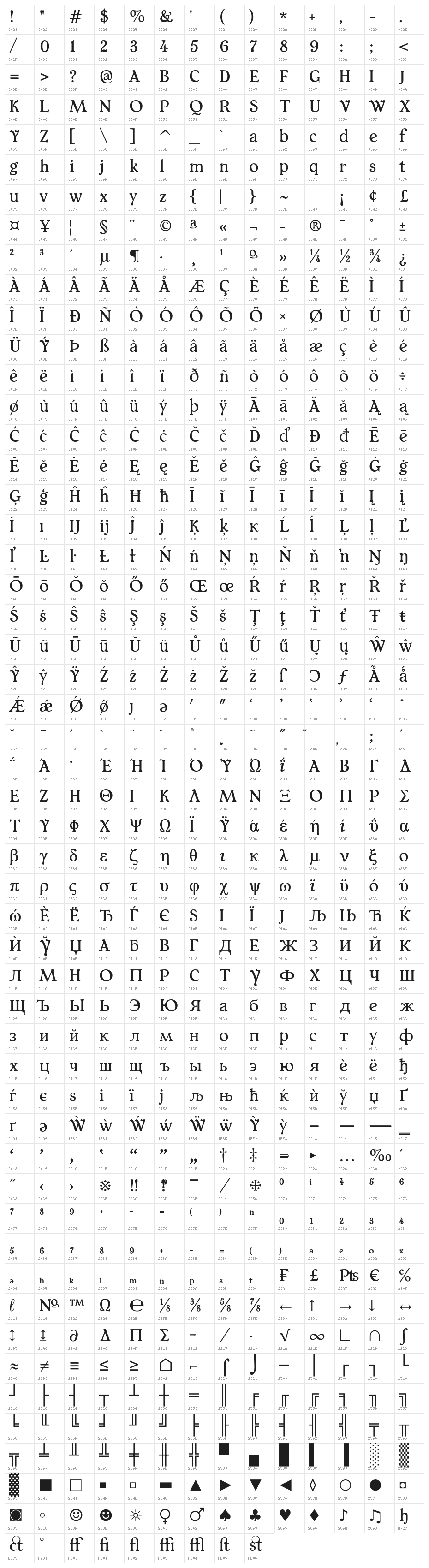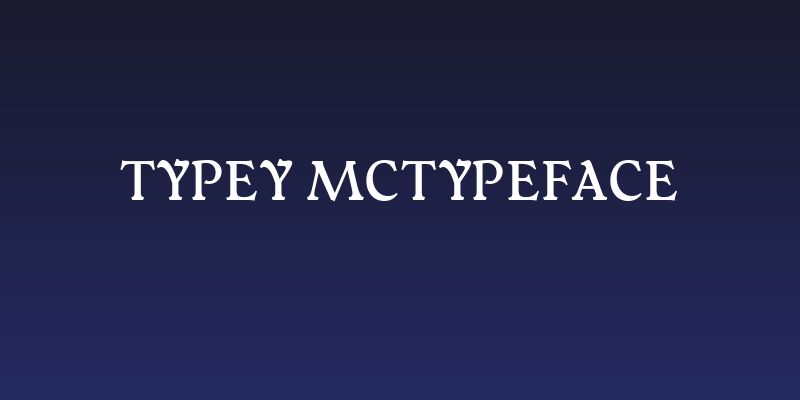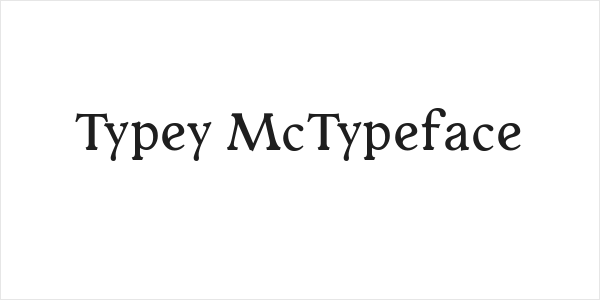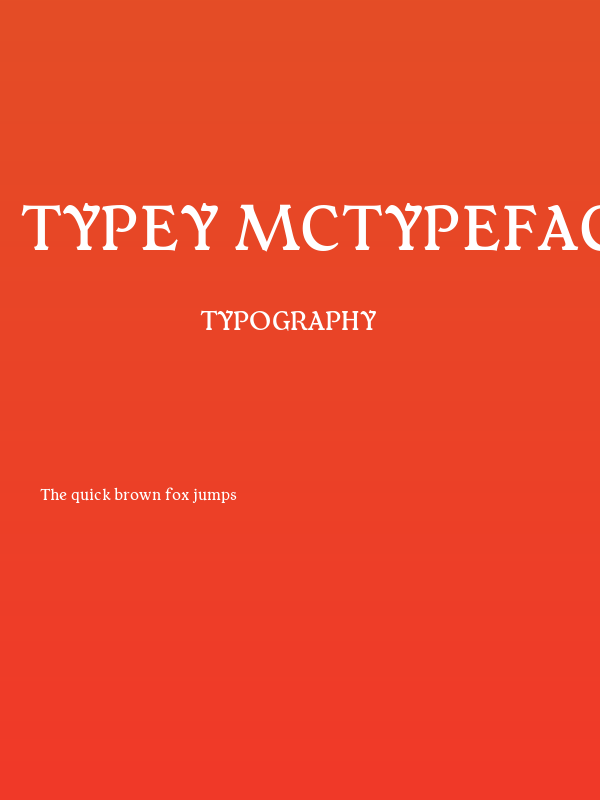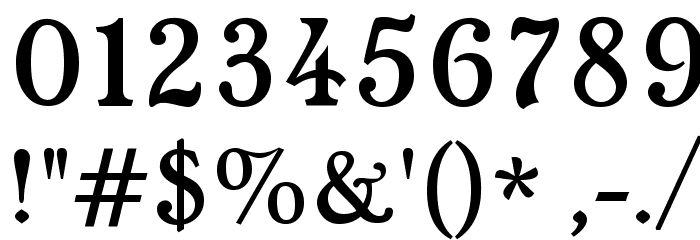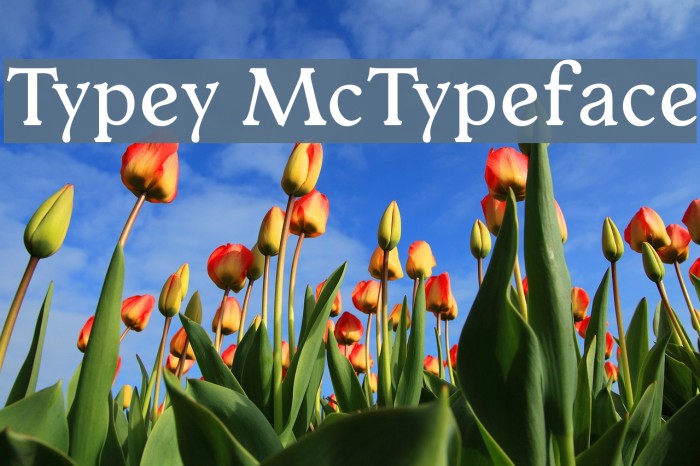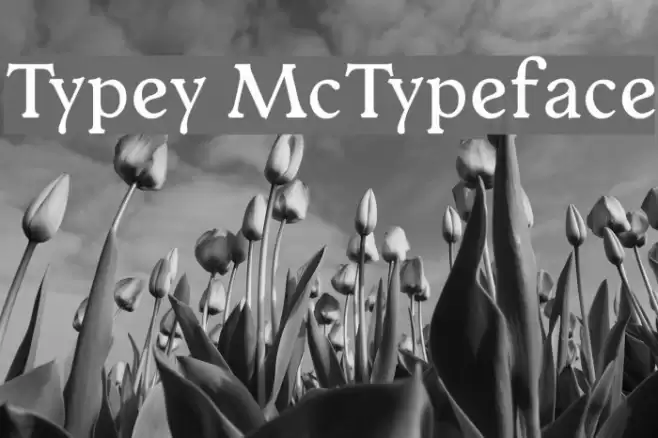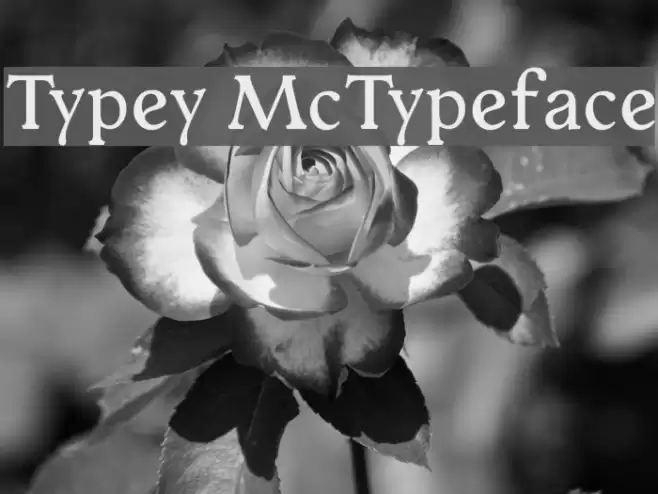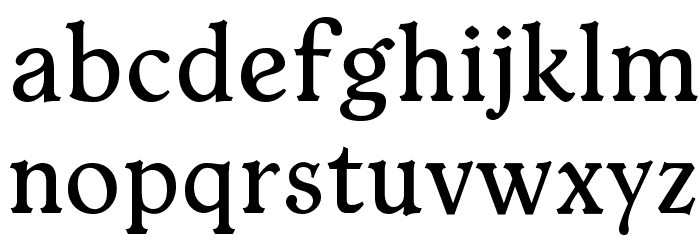
Typey McTypeface Font
✎ Serif
| Kategorien | Serif |
| Gesamtstil | Classic |
| Anwendungsfall | Headlines, Body text, Logos |
| Vorgeschlagene Projekte | Ideal for book covers, formal invitations, branding materials, and editorial design. |